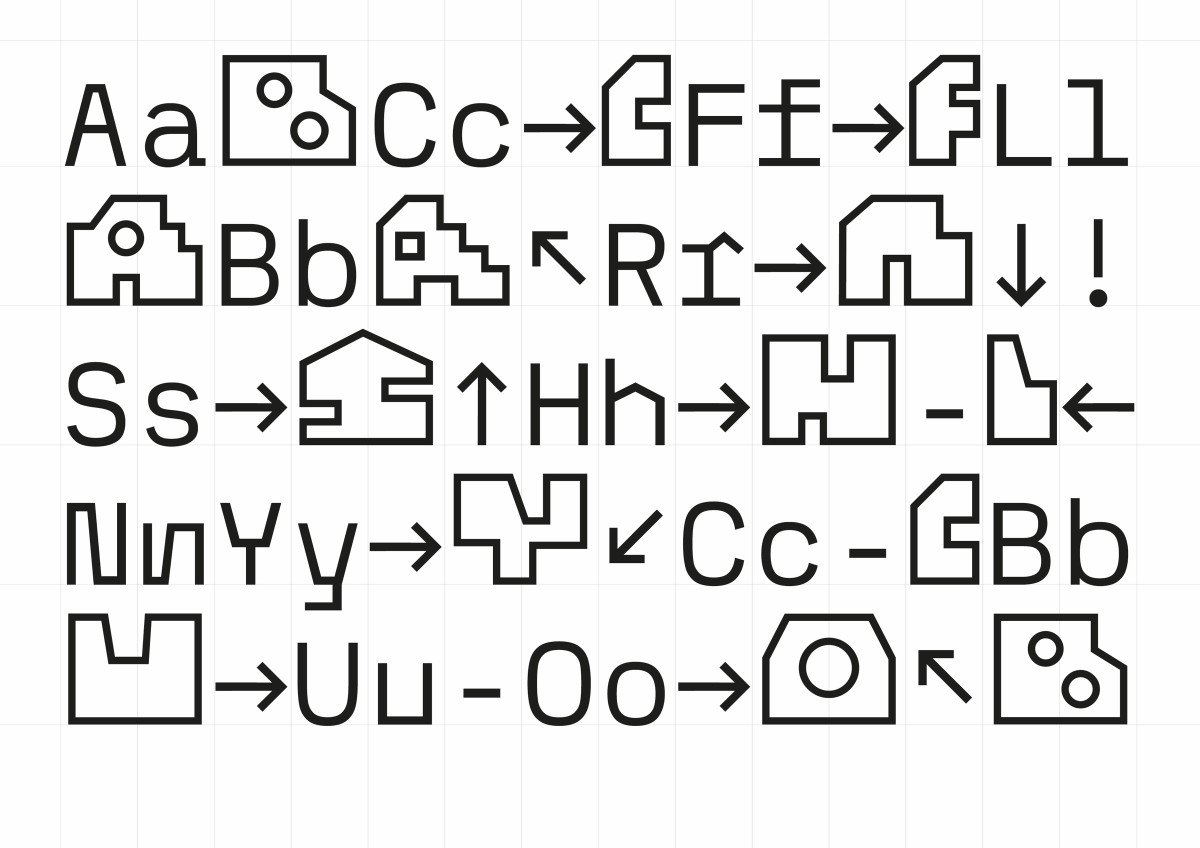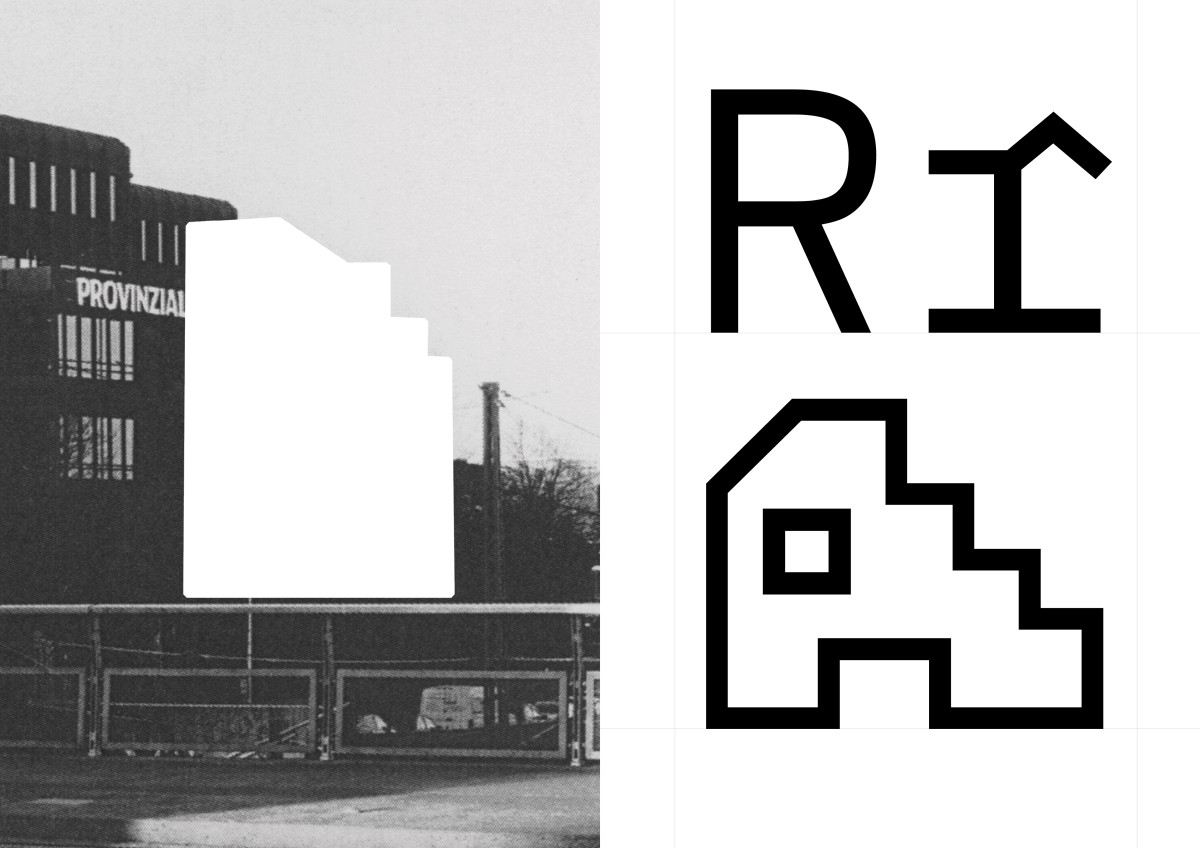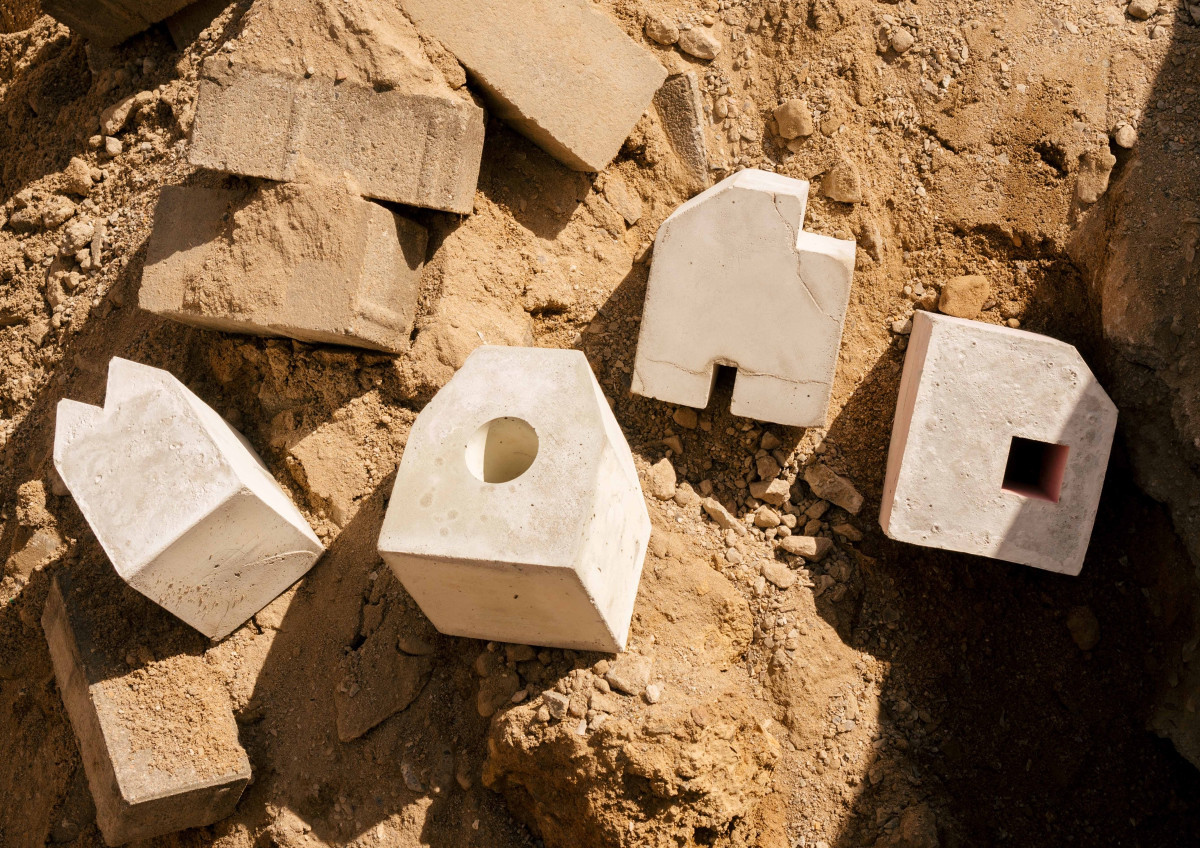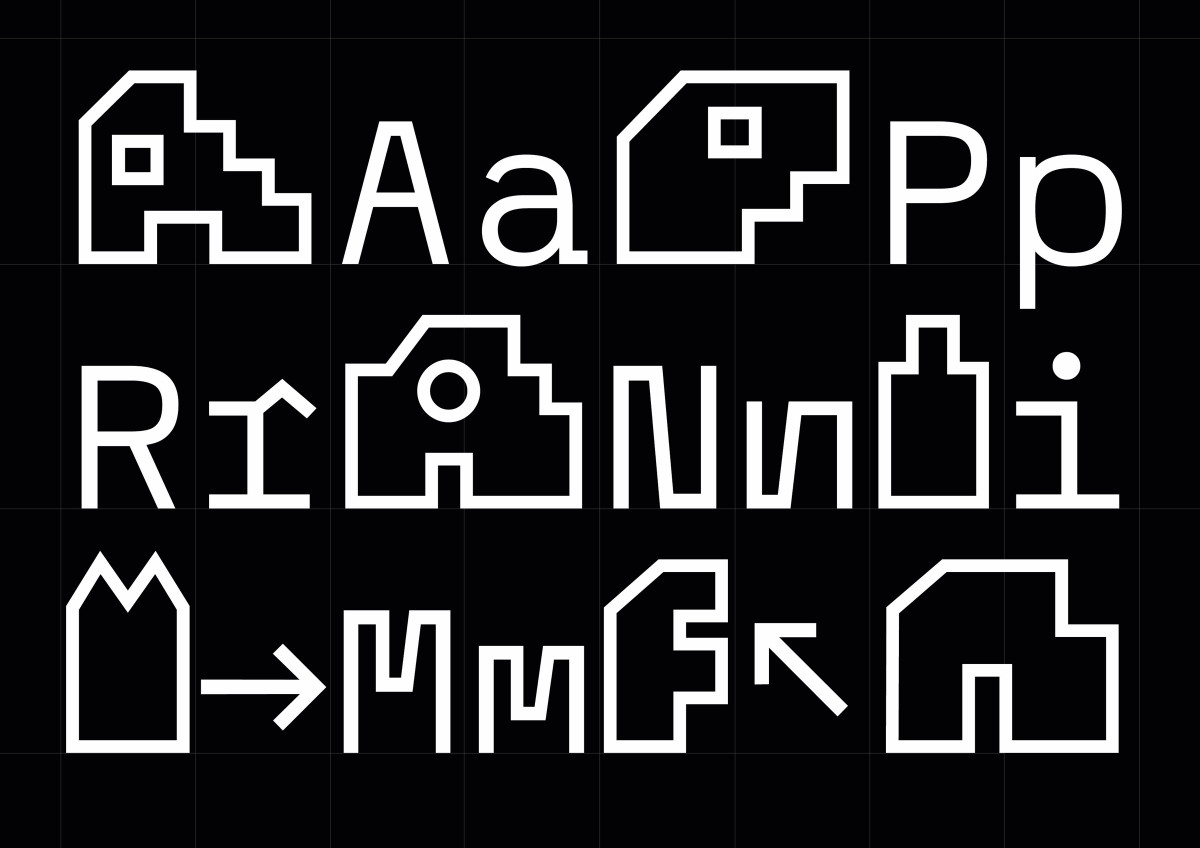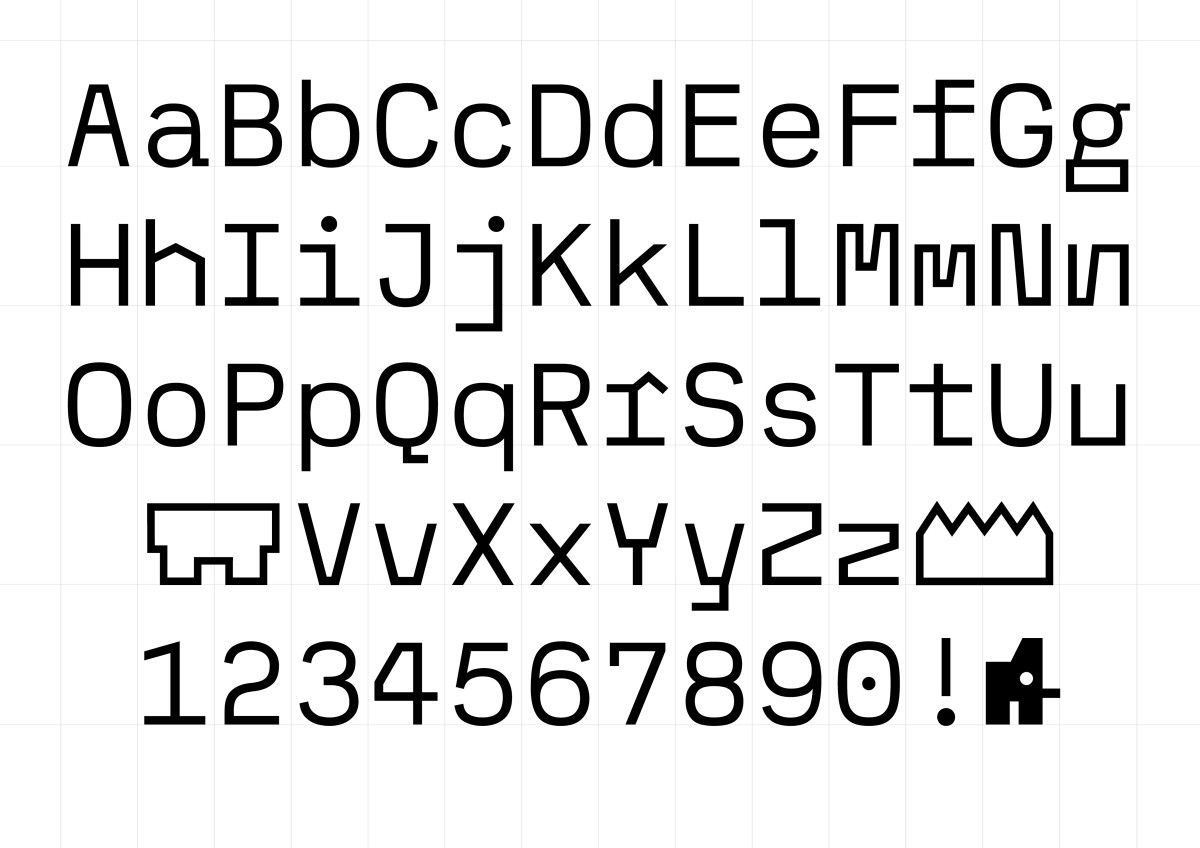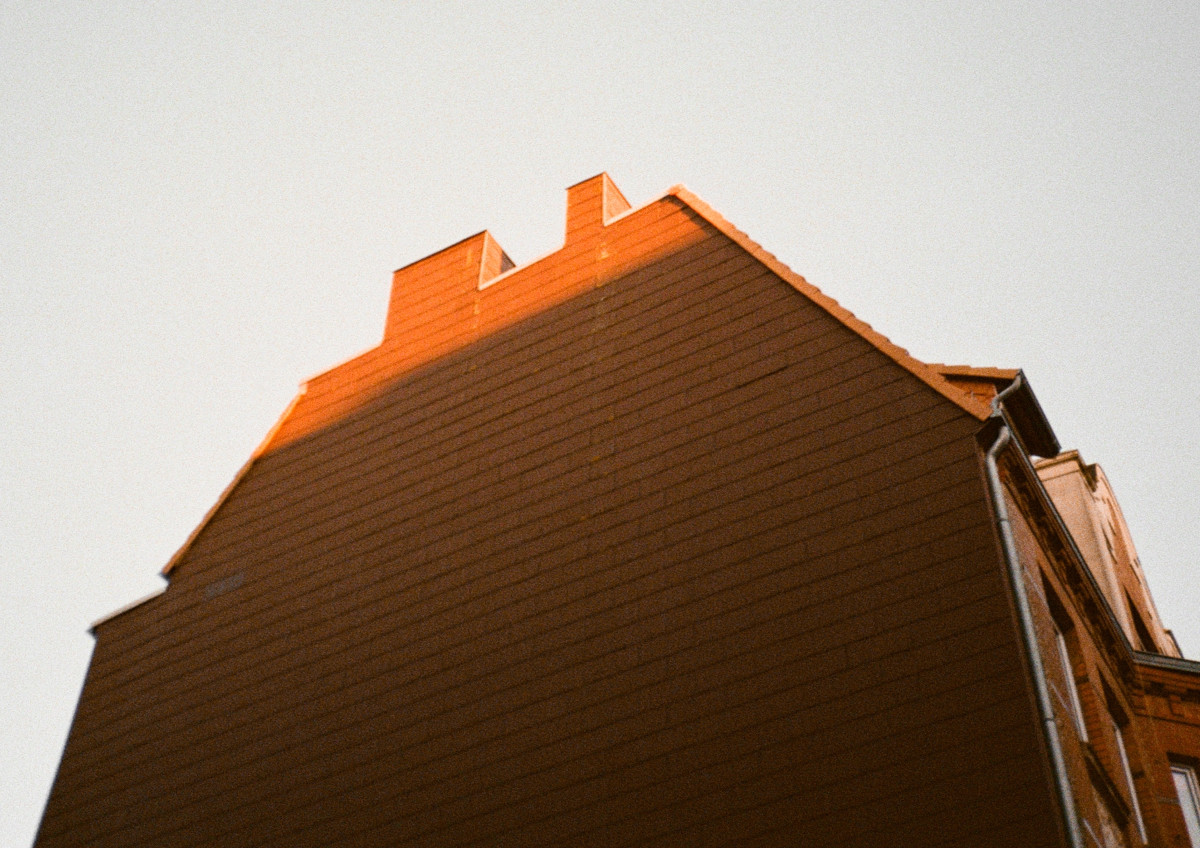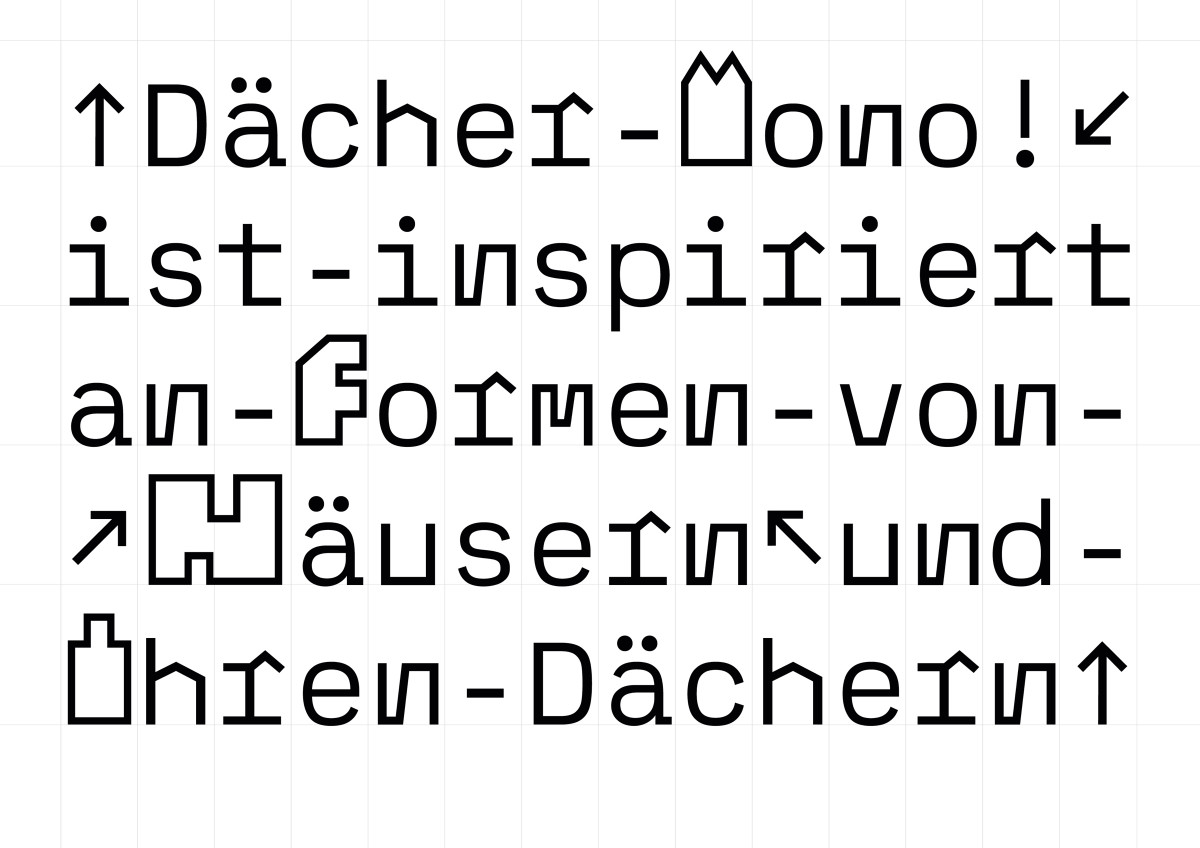
Die Dächer Mono ist eine Monospace Schrift, welche inspiriert ist an Stadtformen. Vorlage für die Mono Schrift und das Stylistic Set sind prägnante Dachformen. So entsteht eine Schrift mit spannenden Stolpersteinen, die sich in den Schreibfluss des Lesens integrieren. Die Schrift umfasst 468 Zeichen mit 5 Schnitten von Light bis Brutal. Das Prozessbuch zum Projekt zeigt wie ich meine Umgebung fotografisch erkundet habe und wie diese Eindrücke mich für die Gestaltung der Schrift inspirierten. In ingesamt 4 Kapiteln begleitet ihr mich in meinem Wahrnehmungsprozess, der Entwicklung sowie der Umwandlung der klobigen Varianten in Beton durch meinen Schaffensprozess und versteht wie die Dächer Mono ihren Ursprung fand.
Dächer Mono is a monospaced typeface inspired by urban forms.
The foundation for both the monospace structure and the stylistic set lies in distinctive rooftop shapes. The result is a typeface full of intriguing stumbling blocks that integrate into the flow of reading. The typeface includes 468 characters and comes in five weights, from Light to Brutal. The accompanying process book documents how I explored my surroundings through photography and how these impressions inspired the design of the typeface. Across four chapters, you’ll follow my journey of perception, development, and the transformation of bulky shapes into concrete forms through my creative process — revealing how Dächer Mono came to life.